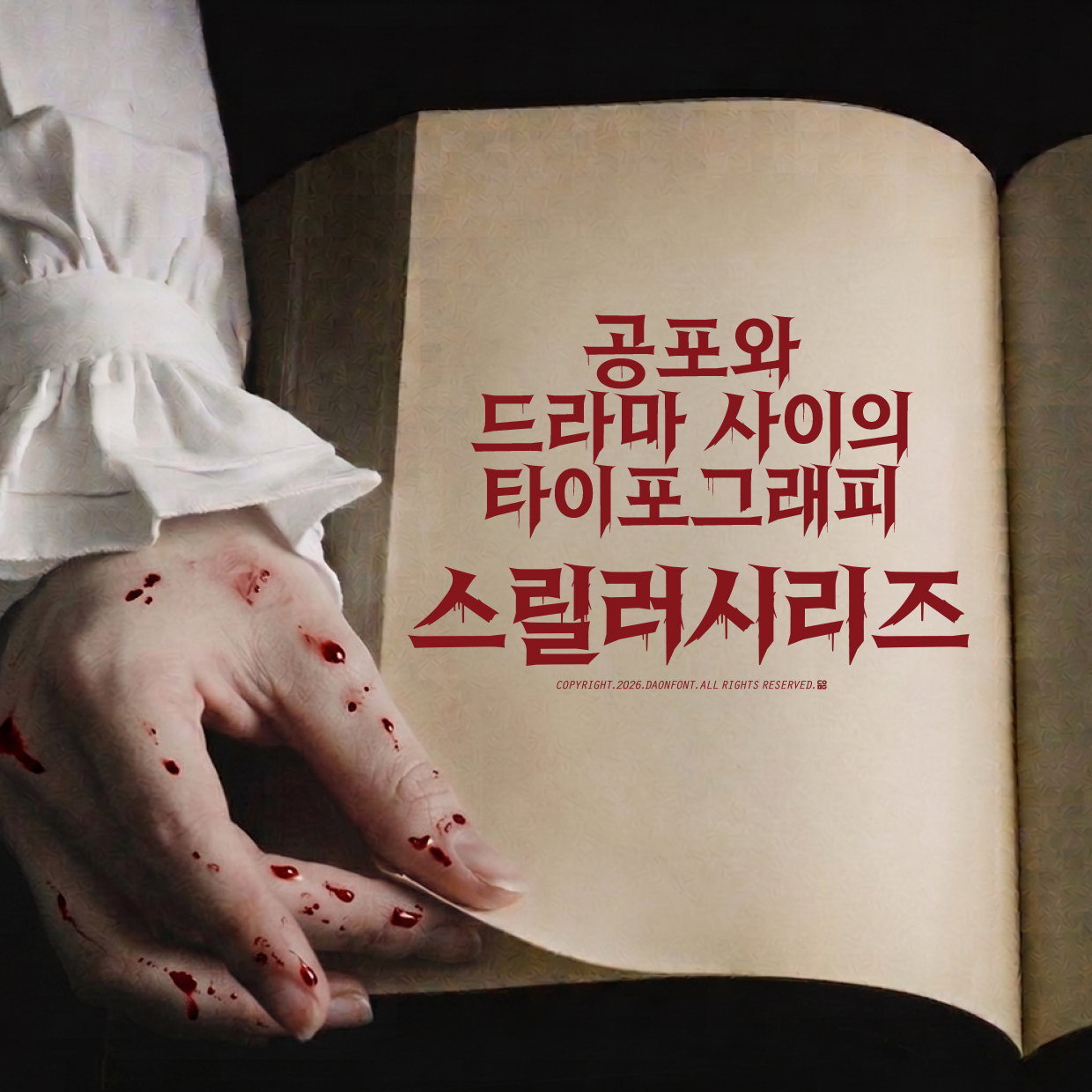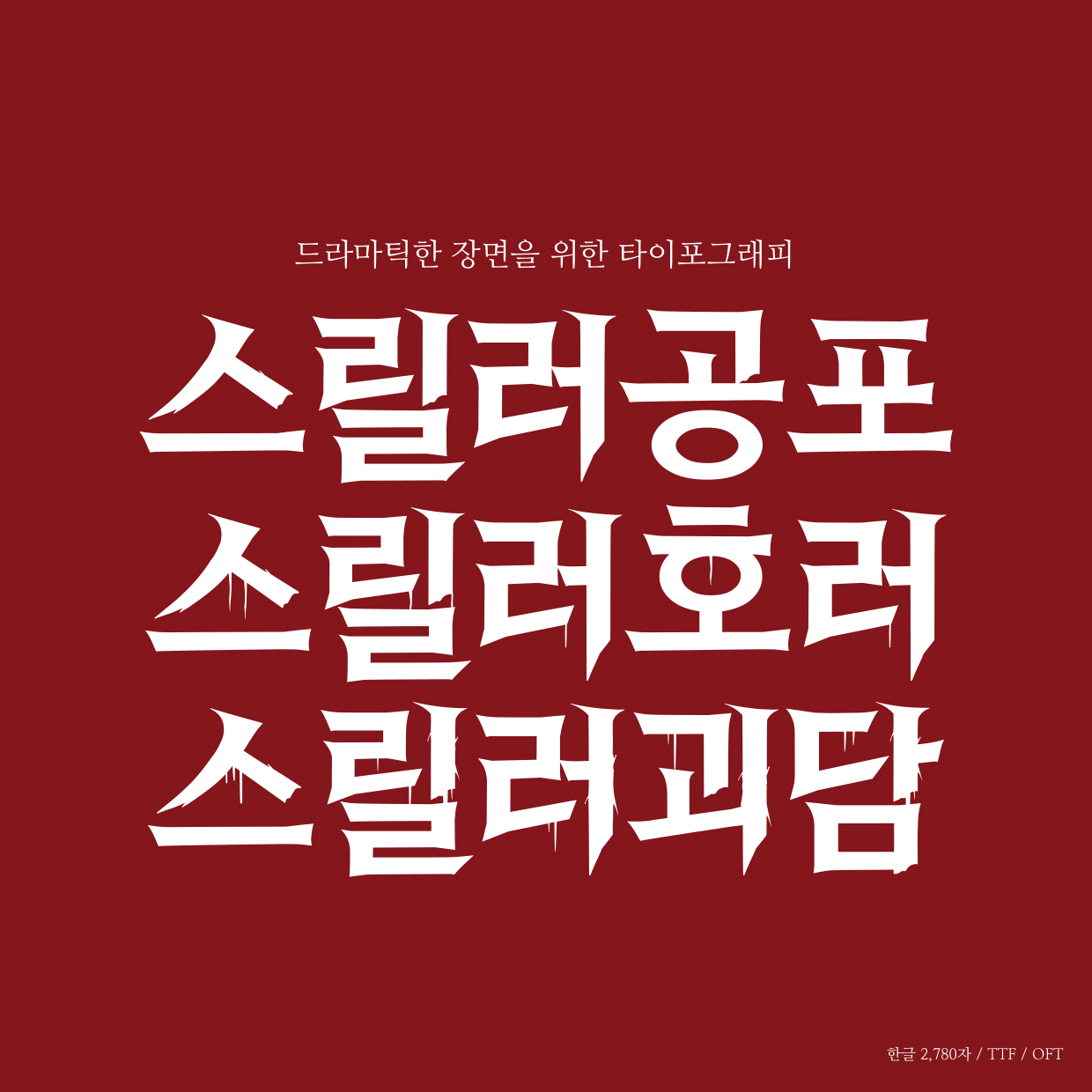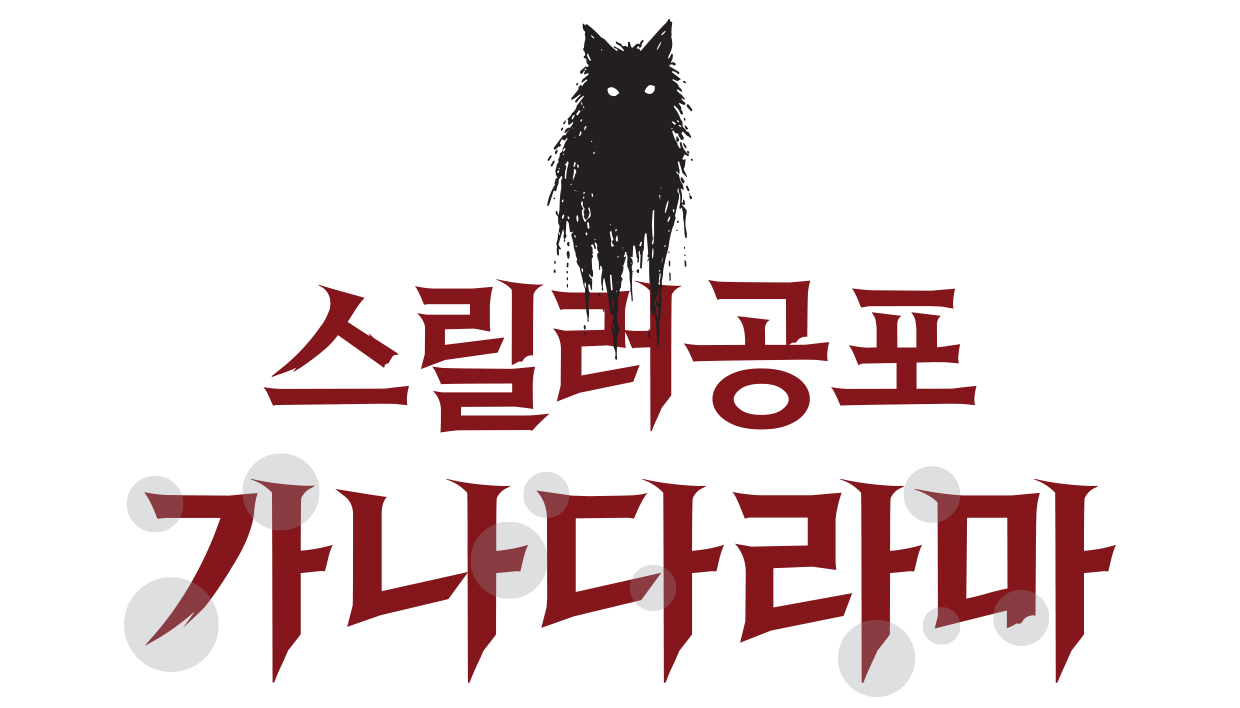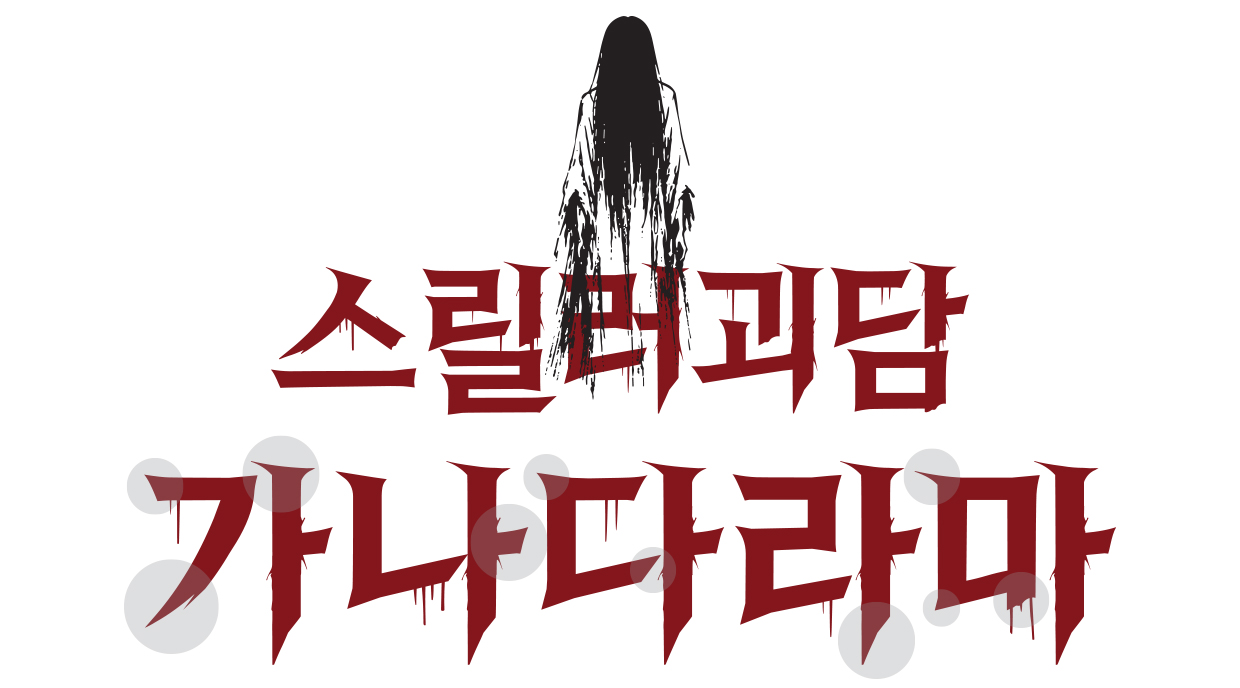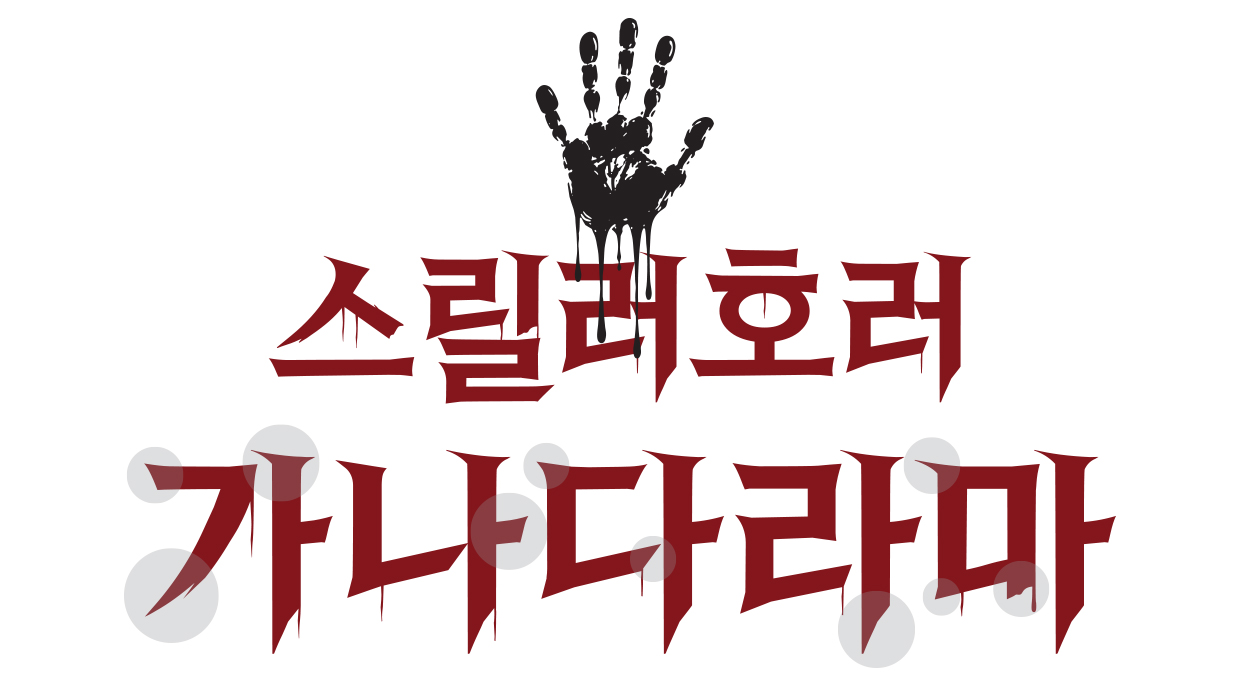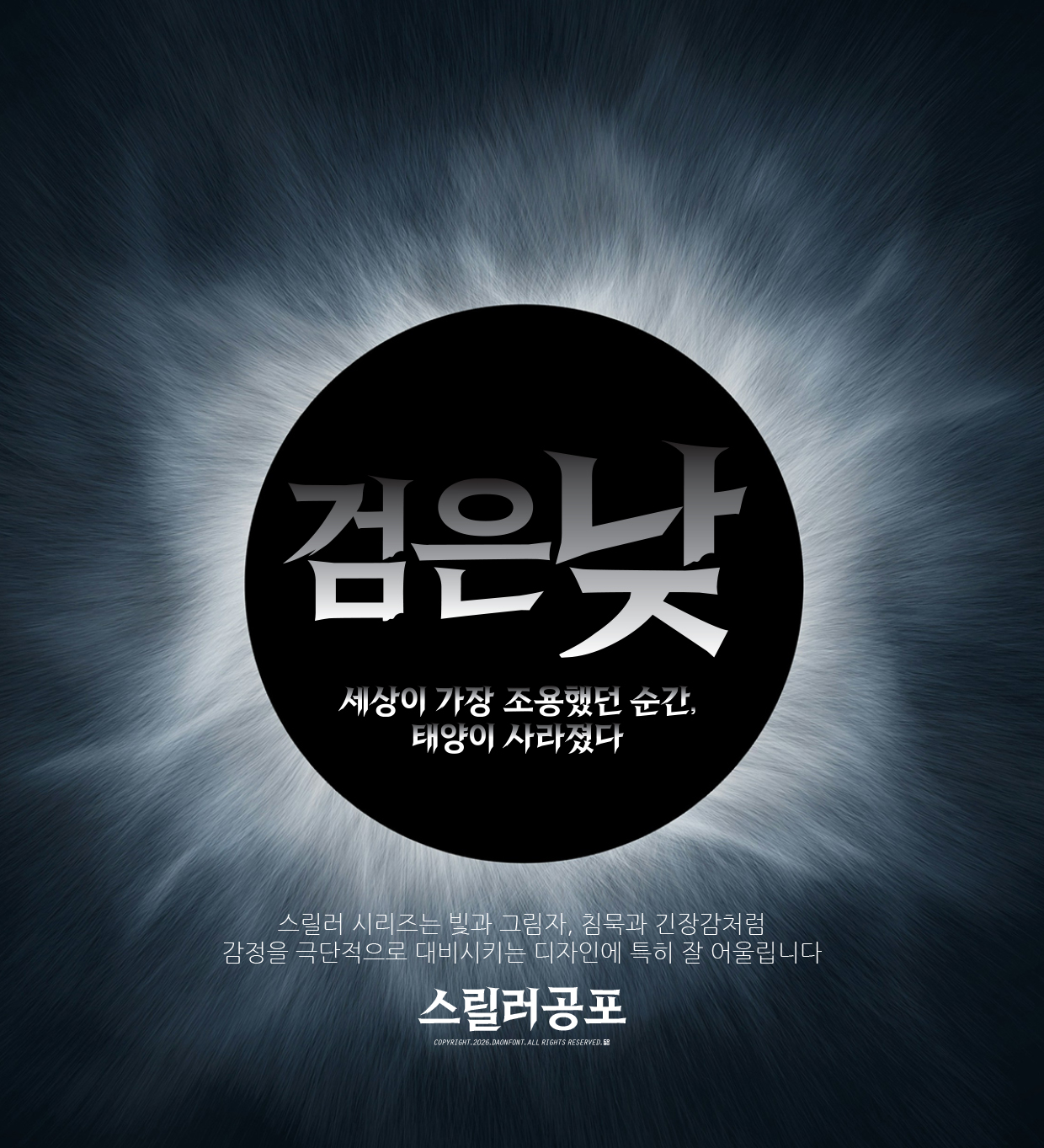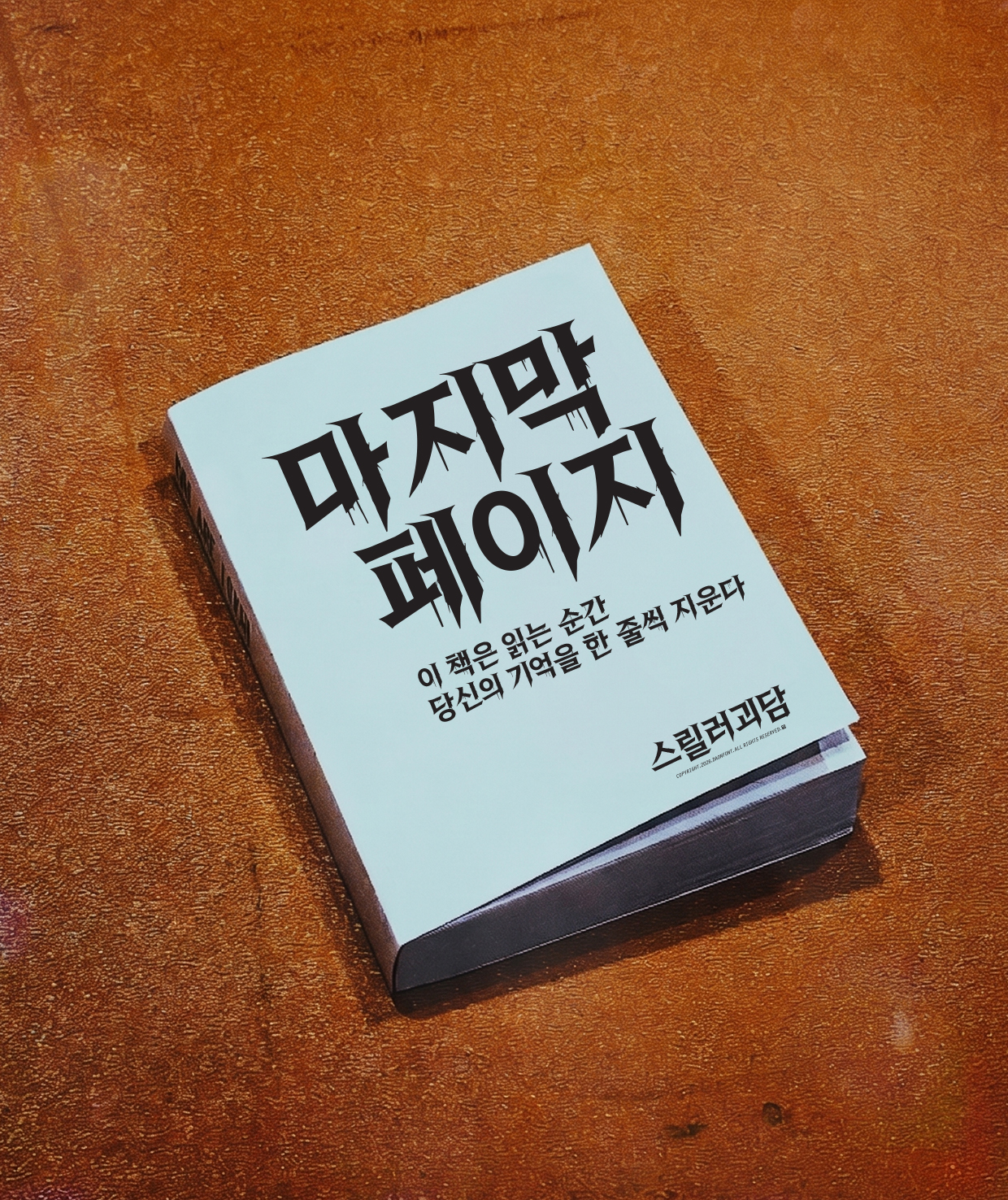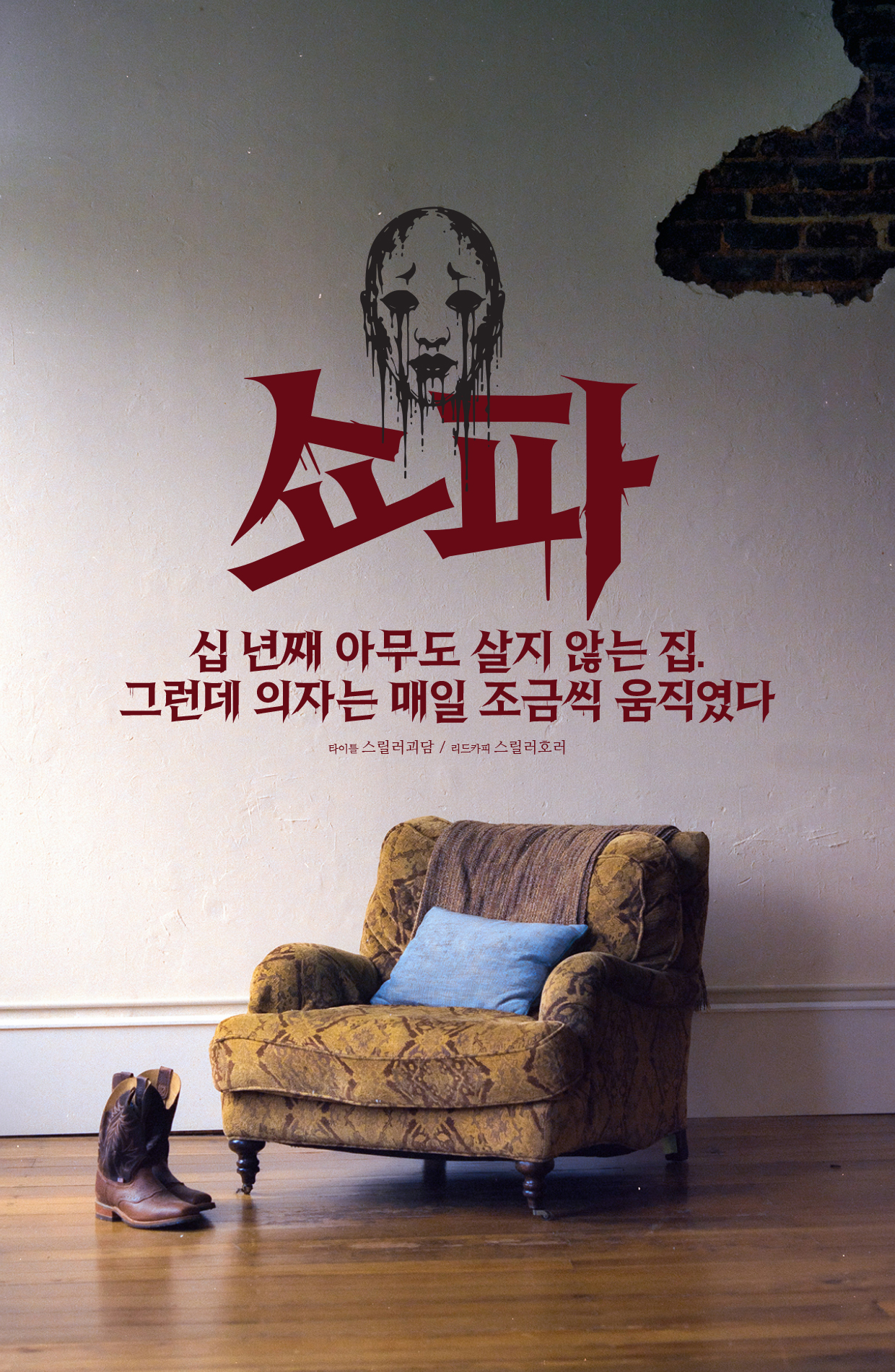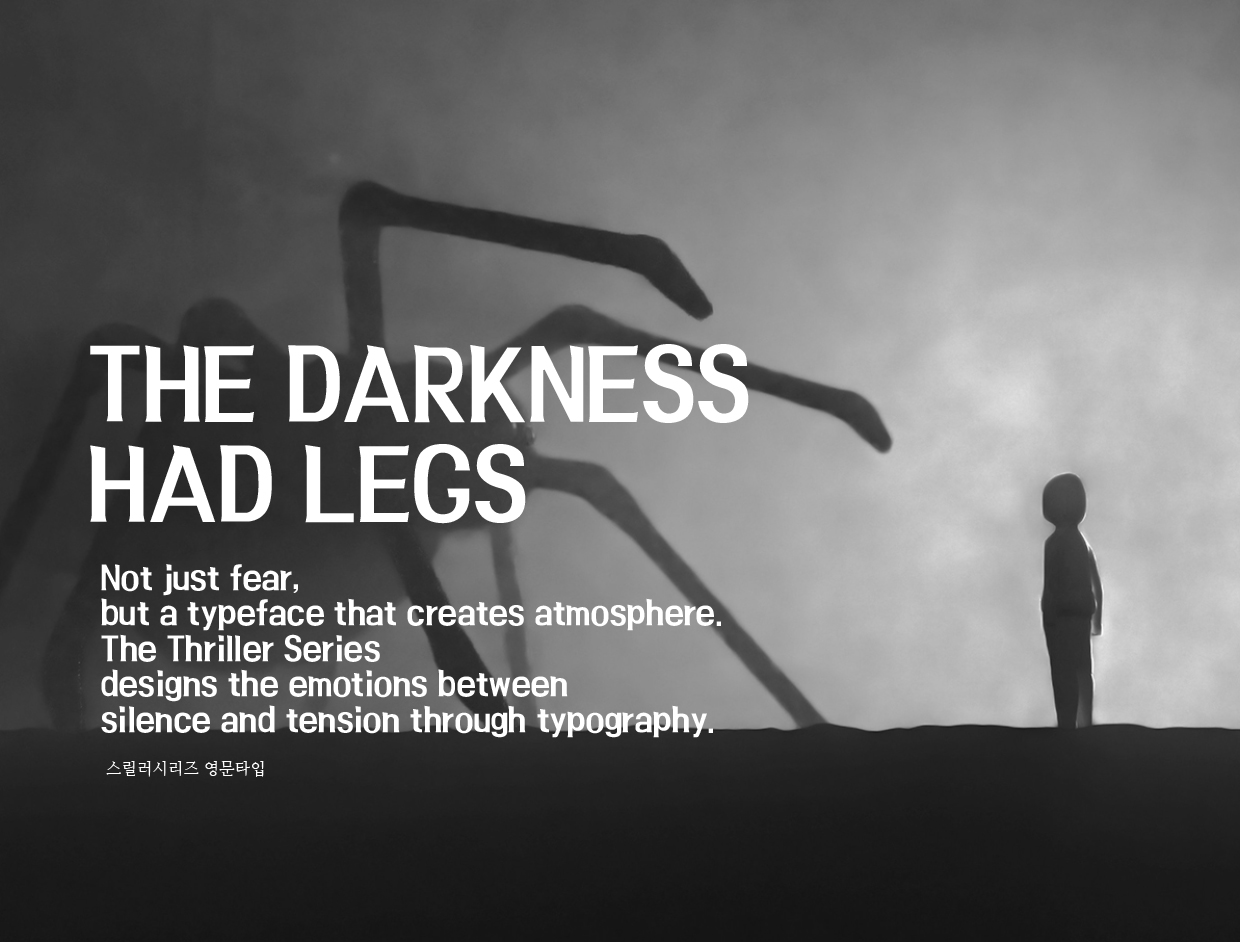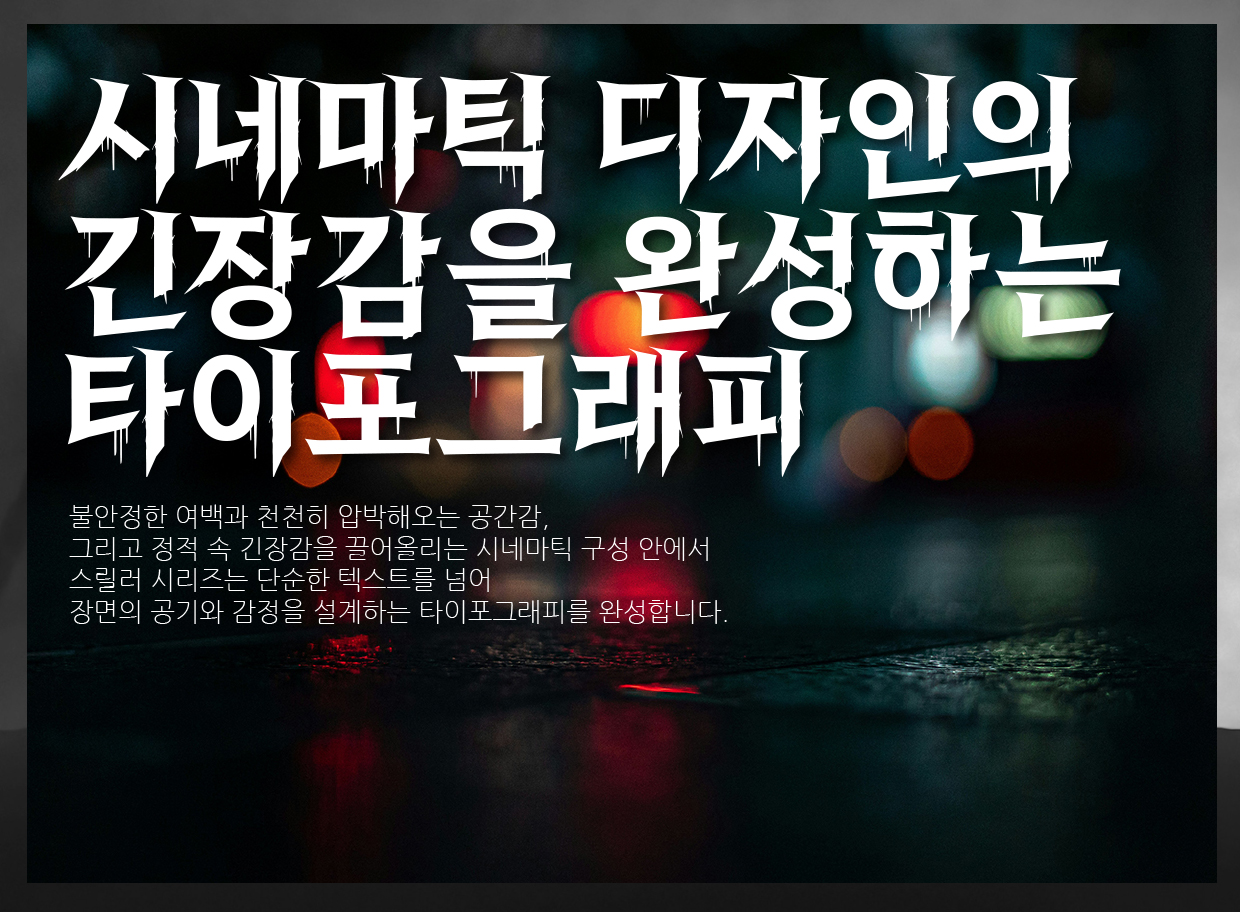
다온폰트 스릴러 시리즈 3종 출시 안내
다온폰트의 새로운 디스플레이 서체 스릴러 시리즈 3종이 출시되었습니다.
스릴러 시리즈는 공포, 호러, 괴담 3종으로 구성된 서체로,
장르 특유의 긴장감과 몰입감을 텍스트만으로 표현할 수 있는 서체입니다.
거칠고 날카로운 질감, 불안감을 자아내는 조형, 강렬한 존재감을 담아낸 스릴러 시리즈는
영화 포스터, 유튜브 콘텐츠, 웹툰, 게임, 방송 자막, 이벤트 홍보물 등
시선을 사로잡아야 하는 다양한 분야에서 활용할 수 있습니다.